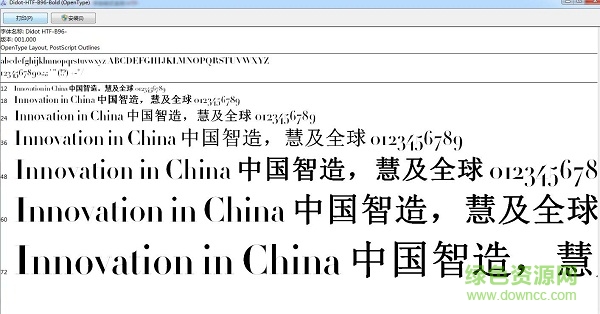
didot htf b96 bold ital
didot htf b96 bold字體是didot字體家族中較粗的一款現(xiàn)代襯線字體,棱角分明,粗細(xì)對(duì)比強(qiáng)烈,有一種高貴冷艷的氣質(zhì),常常出行在時(shí)尚雜志之中,喜歡的朋友歡迎免費(fèi)下載!
didot htf b96 bold ital
didot字體特點(diǎn)
橫向筆畫極細(xì),縱向筆畫很粗,筆畫簡(jiǎn)潔,強(qiáng)調(diào)線豎直,襯線水平、直角彎折,一看就是機(jī)器的產(chǎn)物,感覺非常現(xiàn)代,但又保留了襯線這個(gè)古典元素,Didot是時(shí)尚雜志的寵兒,機(jī)械又富有變化的Didot作為標(biāo)題很漂亮,但字號(hào)太小時(shí)極細(xì)的筆畫很難看清,因此不適合作為正文使用。